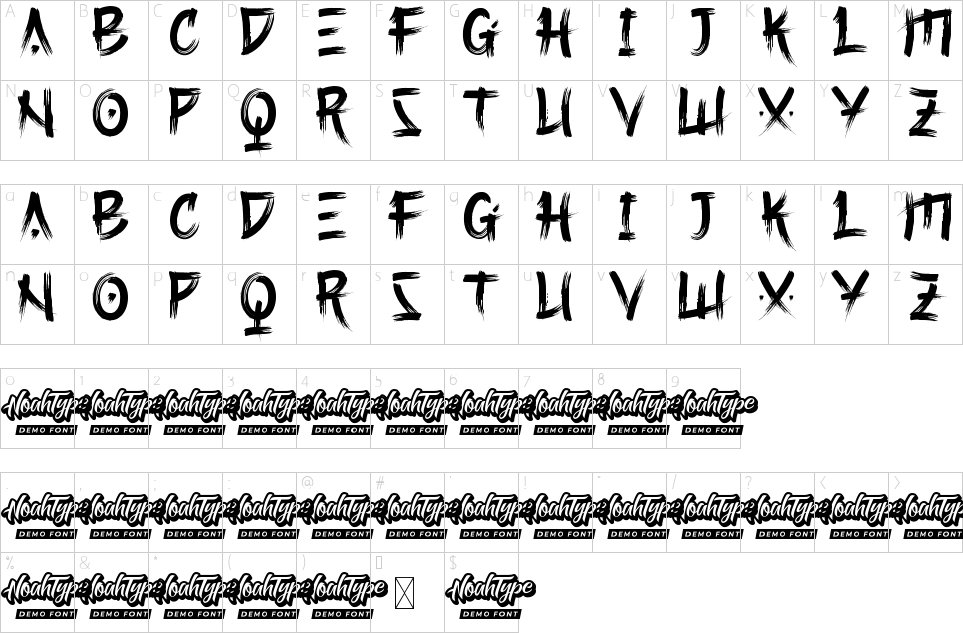
Descubra a tranquilidade e a beleza natural do Japão com Onsen Japan Font. Inspirada na arquitetura tradicional japonesa e pela paz das onsens, esta elegante fonte combina um charme único com alta qualidade de desempenho. Suas linhas fluidas e nuances sutis transmitem tranquilidade e simplicidade ao mesmo tempo em que mantêm a força visual necessária para o texto. Esta fonte é perfeita para designers que buscam uma maneira de expressar harmonia e serenidade, seja em designs de interiores, identidades corporativas ou ilustrações. Seja você um designer profissional ou iniciante, Onsen Japan Font oferece precisão e beleza com a qual pode se orgulhar. Com apenas alguns cliques, transforme seus projetos digitais neste reflexo tranquilo e singular da natureza japonesa.